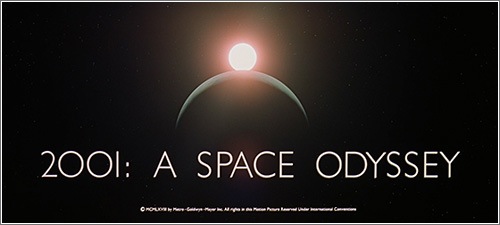
Typeset In The Future repasa las tipografías utilizadas en la ciencia ficción. Por ahora sólo tiene una entrada, pero merece totalmente la pena porque está dedicado a las tipografías de la película 2001: Una odisea del espacio.
En la película 2001: Una odisea del espacio (1968) se utilizan algunos de los tipos de letra más carismáticos y reconocibles empezando por la Gill Sans empleada en el título de la película, con la curiosidad de que los ceros de «2001» en realidad son la letra O.